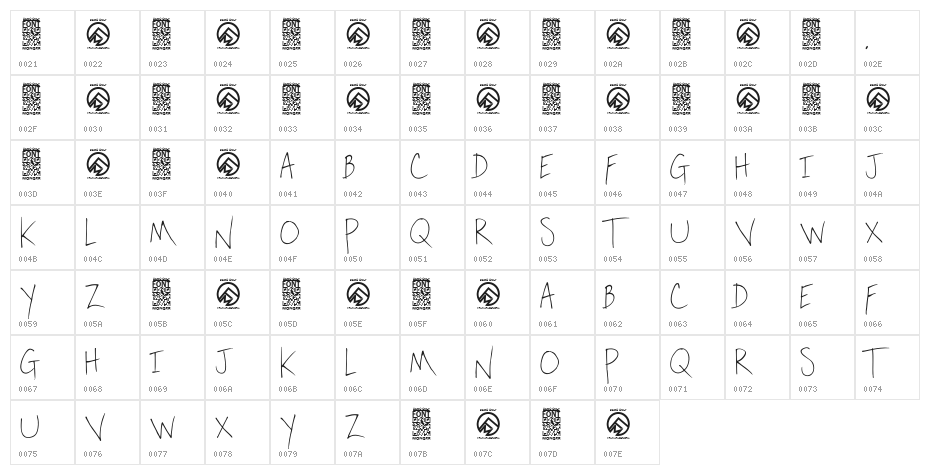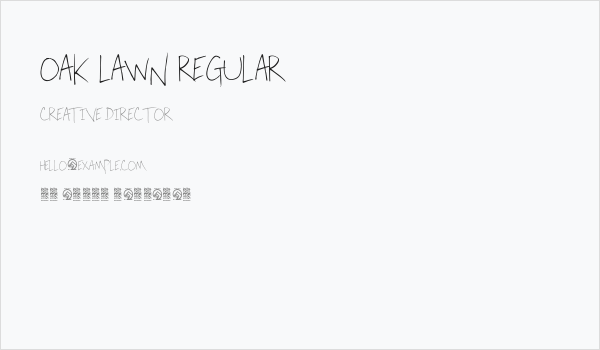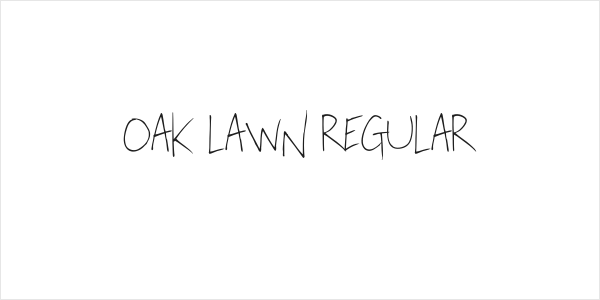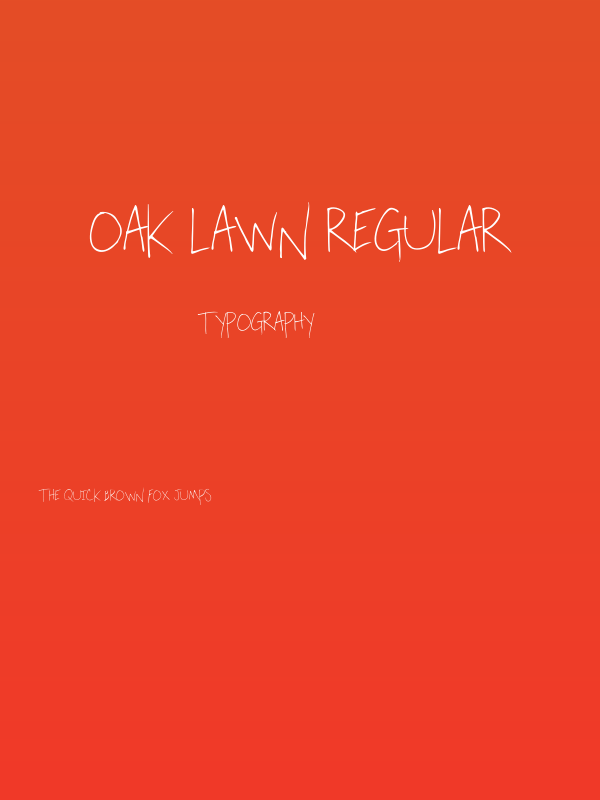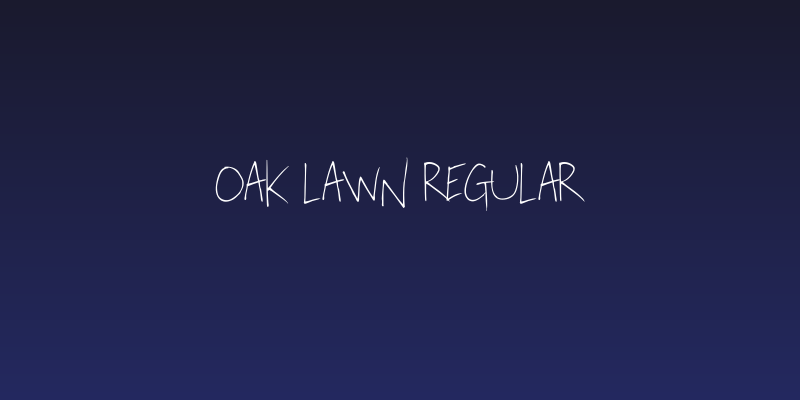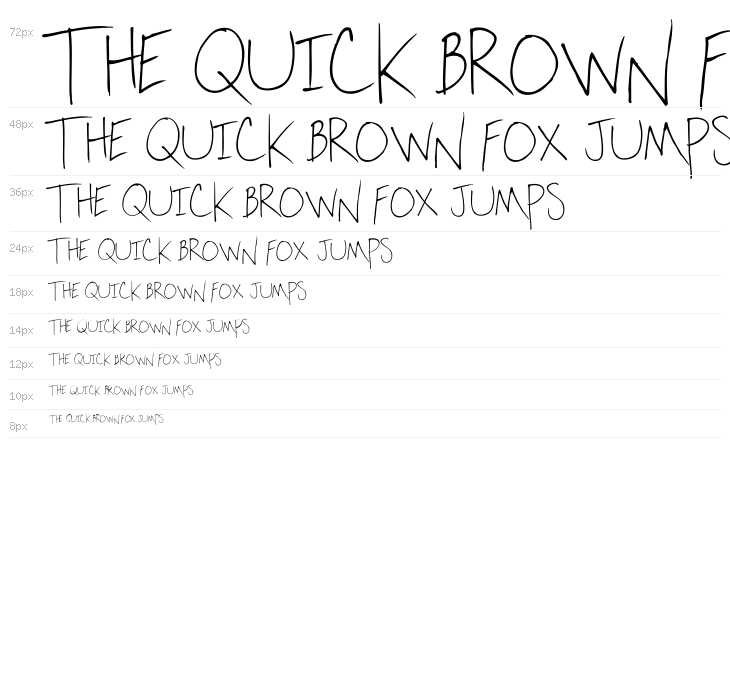
Oak Lawn Regular Font
| Stile generale | Casual, Playful |
| Caso d'uso | Headlines, Creative projects, Personal branding |
| Progetti proposti | Ideal for greeting cards, invitations, personal branding, and creative projects that require a handwritten touch. |